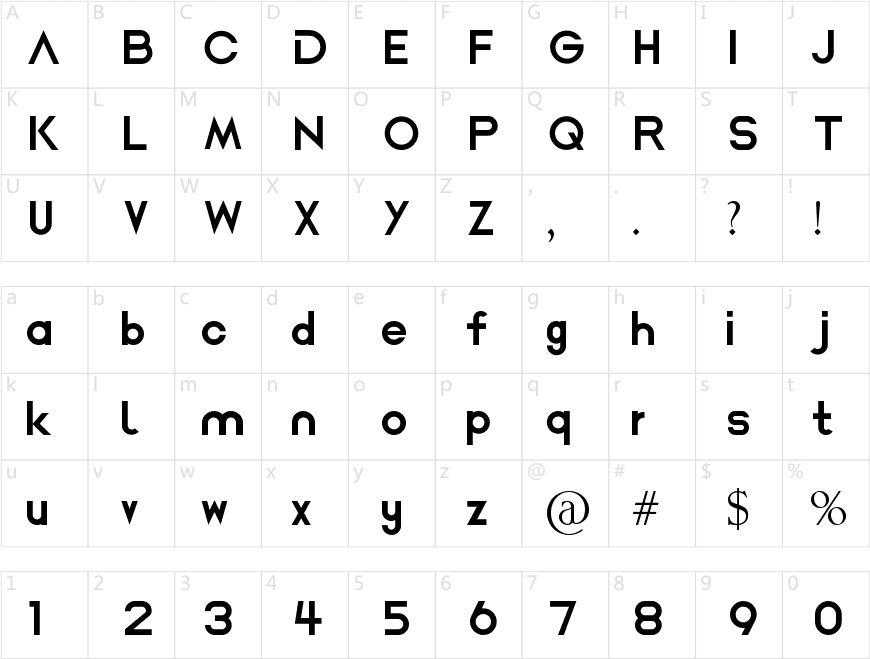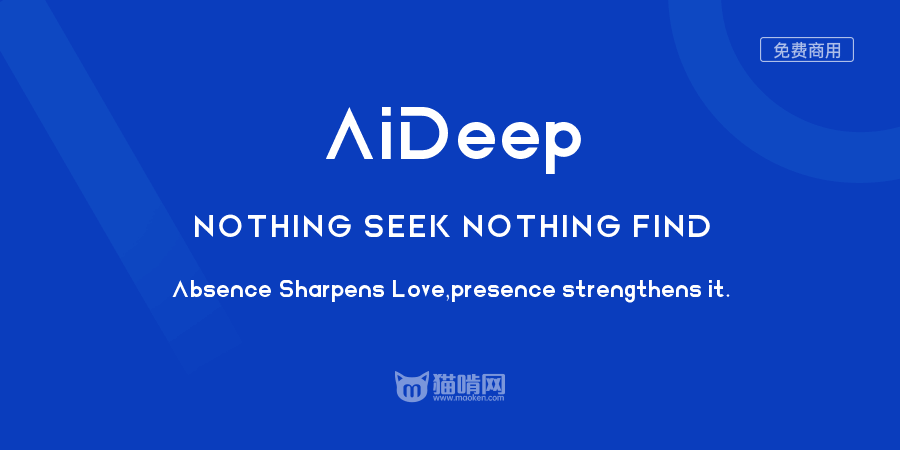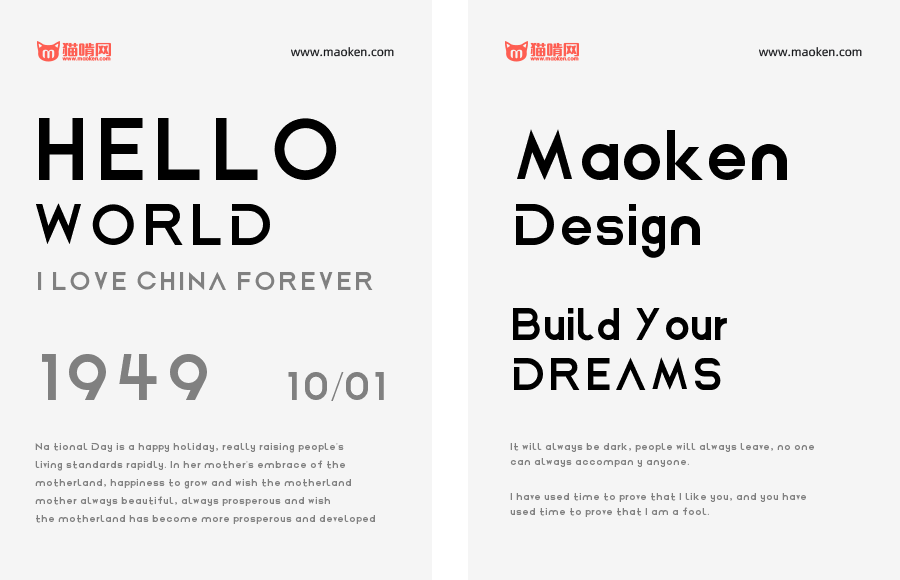
AiDeep
字体作者:AiDeep (中国) 字体字重:1个
团队今年定位国际化,将大部分业务都定位为英文命名,所以考虑了品牌VI的标准化,为了方便,所以做了一整套字体,方便日后新业务出现还在为了各种LOGO设计而费脑筋,设计者为网络尖刀UED团队,小伙子。
中文字体做了700多个,实在做不动了,所以先发了26个英文大写+26个英文小写,额外0-9这10个阿拉伯数字。